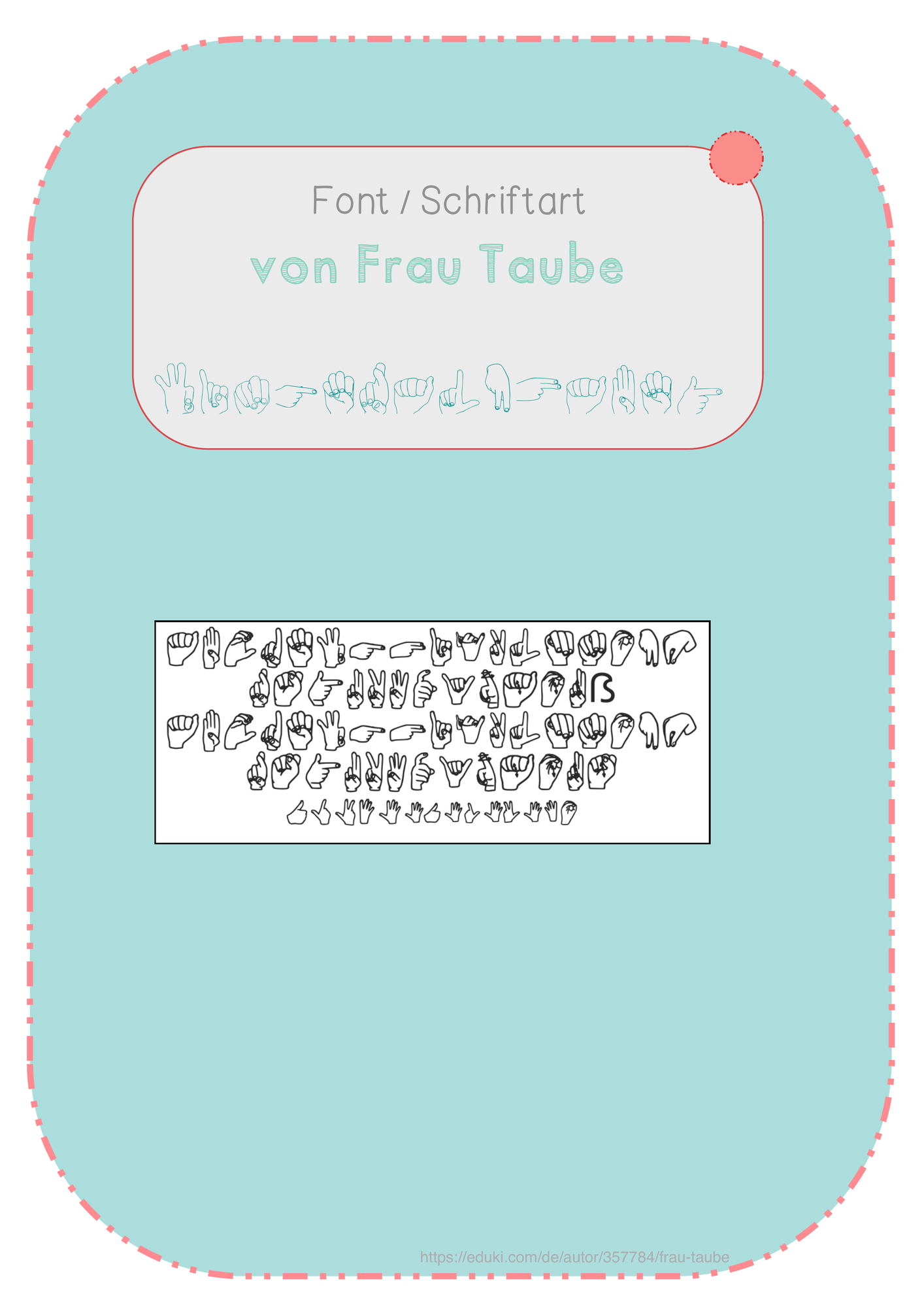
Fördermaterial/Inklusion - Fingeralphabet - Font - Schrift - Gebärdensprache - Frau TAUBe - Deckblatt
Entdecke Fingeralphabet-Font – die perfekte Lösung für das Schreiben im Fingerakphabet. Mit vollständiger Abdeckung von Buchstaben, Ziffern 0-9, sowie speziellen Darstellungen für "SCH" und "CH". Einfache Bedienung dank klarer Tastenbelegung.
Fingeralphabet - Font - Schrift - Gebärdensprache